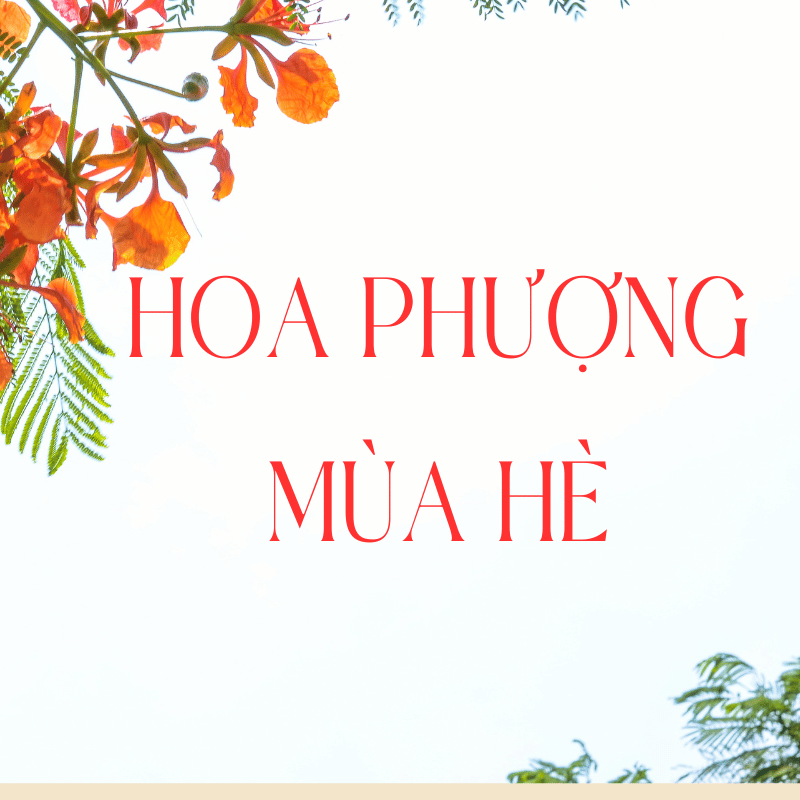
Font Việt hóa FMP Super Pulp
Font Việt hóa FMP Super Pulp  – Phong Cách Retro Độc Đáo Cho Thiết Kế
Font Việt hóa 1FTV VIP Super Pulp là bộ font chữ mang phong cách retro ấn tượng, được thiết kế dành riêng cho dân sáng tạo. Với nét chữ bo tròn, đường nét mềm mại và hiệu ứng vintage, font chữ này phù hợp với các dự án poster, logo, bìa sách, hoặc thiết kế quảng cáo mang hơi hướng cổ điển nhưng vẫn trẻ trung.
Font Việt hóa FMP Super Pulp
Đặc điểm nổi bật Font Việt hóa FMP Super Pulp :
• Phong cách độc đáo: Lấy cảm hứng từ những mẫu quảng cáo thập niên 60-70, Super Pulp mang đến sự hoài cổ nhưng vẫn hiện đại.
• Hỗ trợ tiếng Việt: Font được Việt hóa chuẩn, đầy đủ dấu, phù hợp với mọi dự án trong nước.
• Đa dạng ứng dụng: Dùng cho thiết kế in ấn, digital art, branding, hoặc social media.